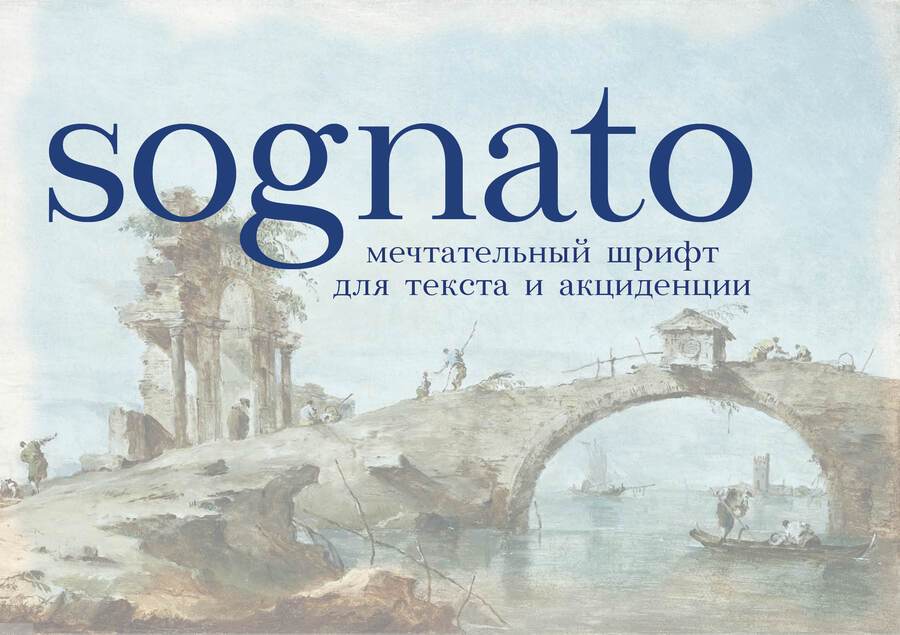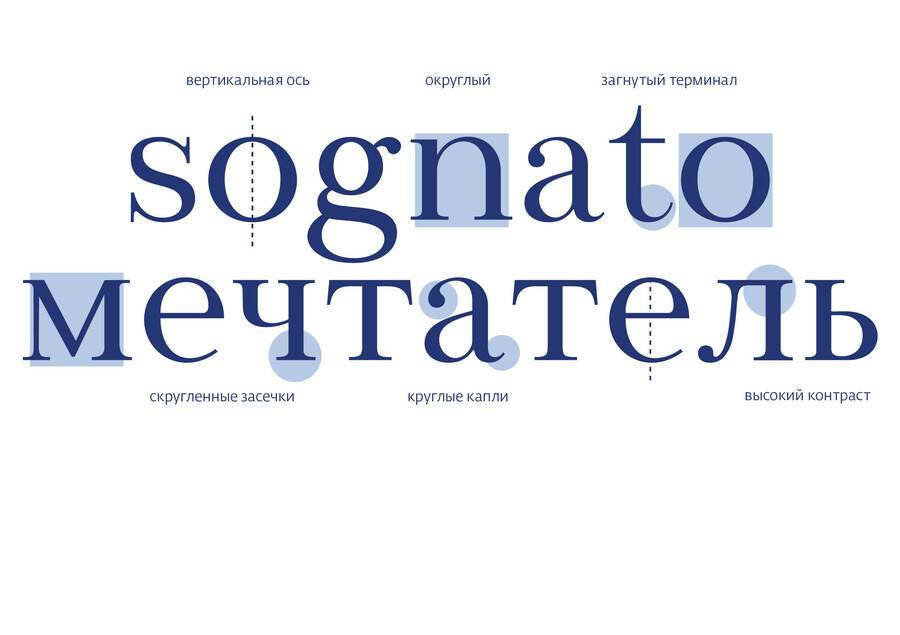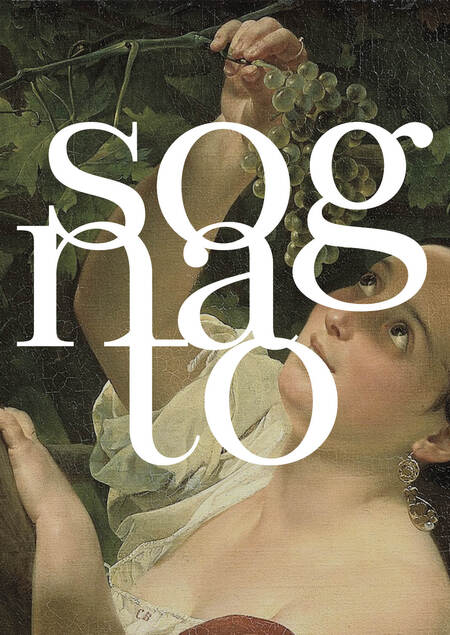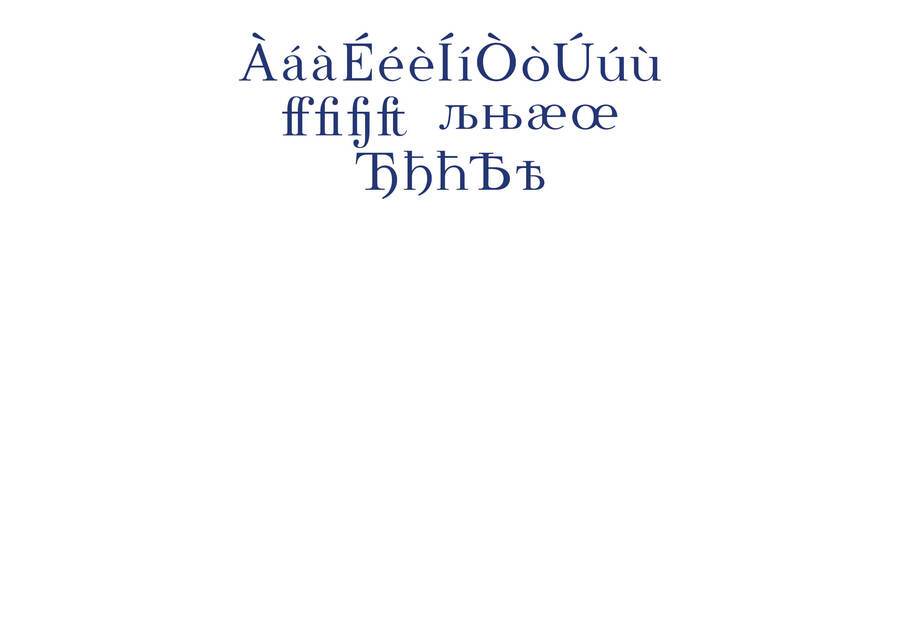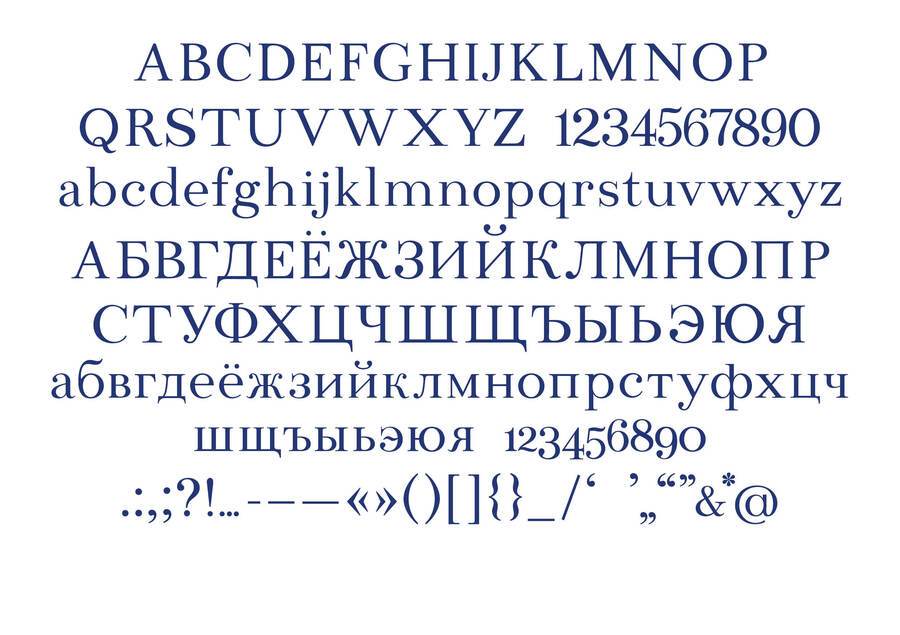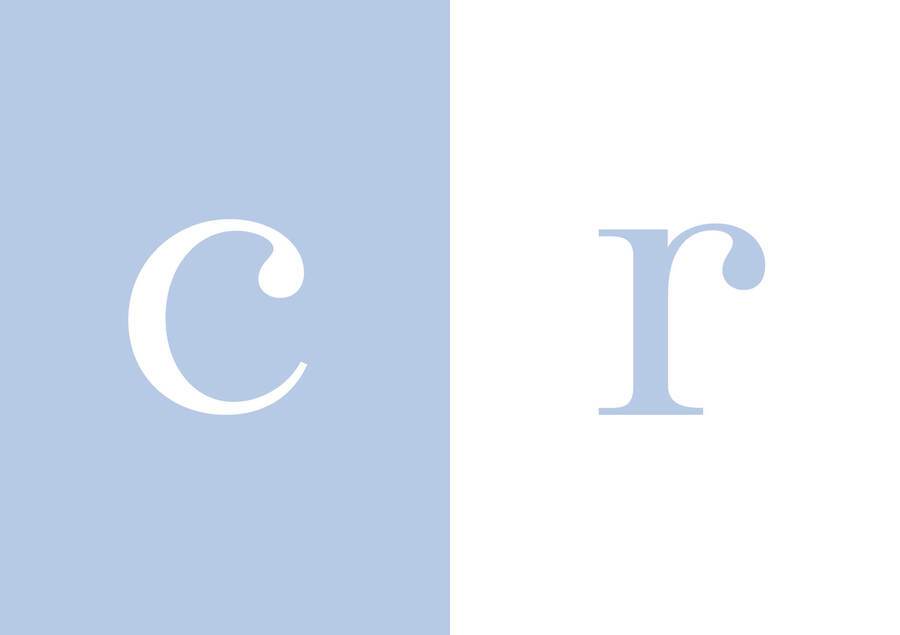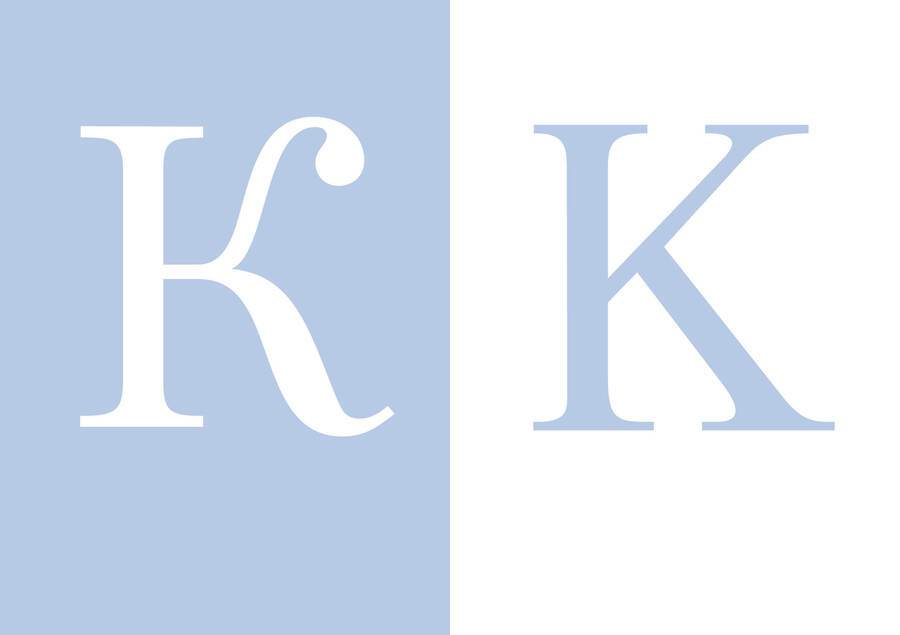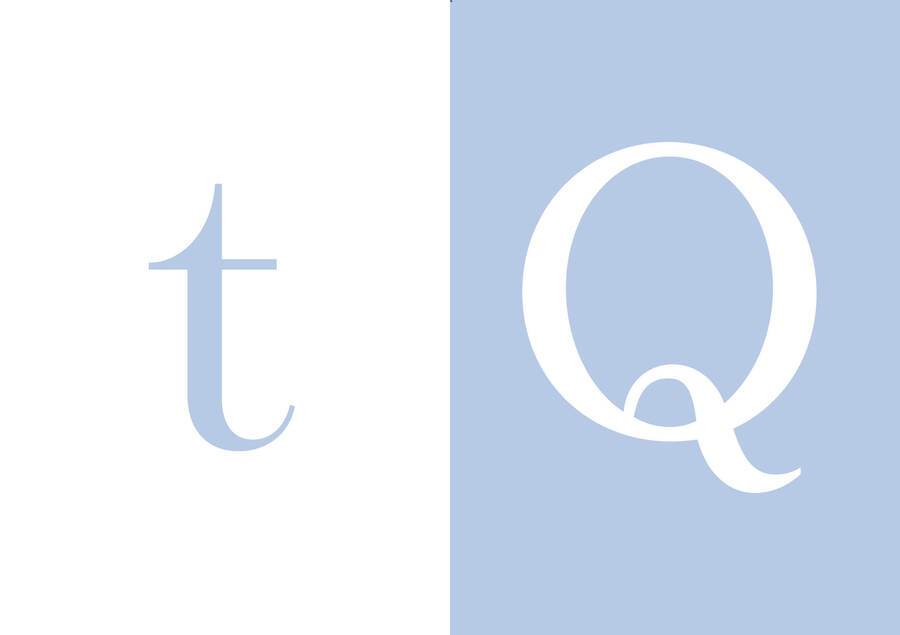
sognato — мечтательный шрифт для текста и акциденции
sognato (от ит. sognare — мечтать) — округлый широкий шрифт, основанный на классе шотландских антикв. Элегантный и немного загадочный шрифт предназначен как для набора длинных текстов, так и для заголовков и акциденции. Подходит для набора книг в жанре фэнтези и брендинга в сфере искусства и моды. Шрифт обладает довольно высоким контрастом штрихов и имеет скругленные засечки. Поддерживает кириллицу и латиницу, имеет диакритику, лигатуры, а также минускульные и маюскульные цифры.